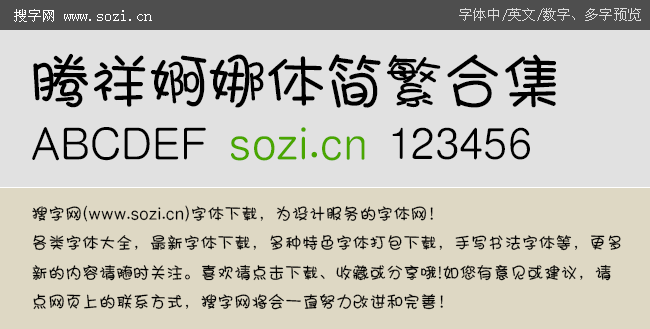
騰祥婀娜體簡繁合集
搜字網(wǎng)提供一款騰祥婀娜體簡繁合集中文藝術(shù)字體下載,騰祥婀娜體是一款設(shè)計精美,有著美好造型和姿態(tài)的騰祥字體,婀娜多姿如少女的形態(tài),童趣橫生給人舒適視覺,整體效果非常的出色,且字庫完整,可用于印刷出版、包裝設(shè)計、廣告設(shè)計、網(wǎng)頁設(shè)計等。